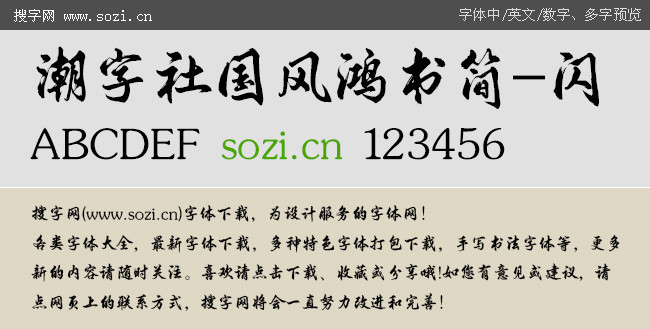
潮字社國(guó)風(fēng)鴻書簡(jiǎn)-閃
搜字網(wǎng)提供一款潮字社國(guó)風(fēng)鴻書簡(jiǎn)-閃中文字體下載,潮字社國(guó)風(fēng)鴻書簡(jiǎn)-閃是一款個(gè)性書法藝術(shù)字體,連貫的字跡顯得干練而不凌亂,清新簡(jiǎn)明,具有很好的視覺感,效果嚴(yán)謹(jǐn)大氣,可用于出版和印刷,文學(xué)雜志,海報(bào)設(shè)計(jì)等應(yīng)用。(本字體為個(gè)人非商用版,商用請(qǐng)聯(lián)系作者購買授權(quán))